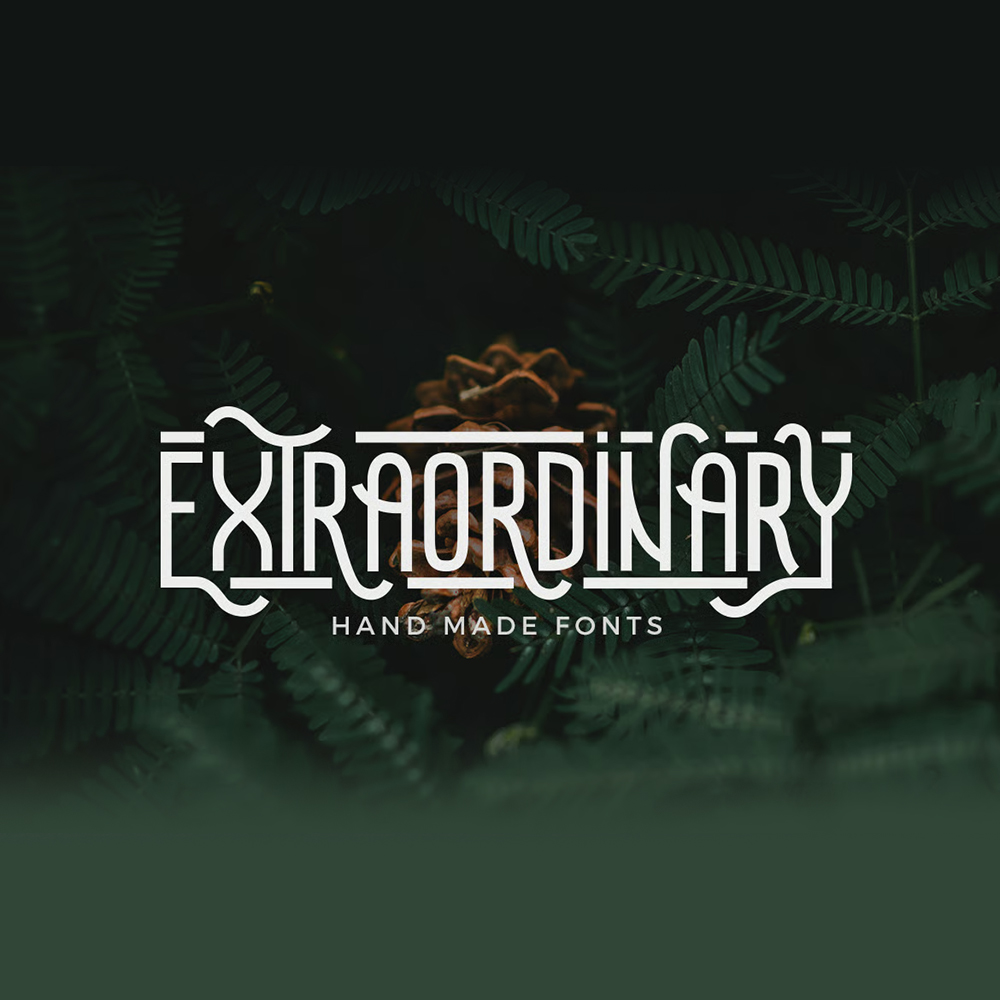
فونت پرمیوم و انگلیسی Extradionary Font یکی از بهترین فونتهای دستنویس ارائه شده میباشد. Extradionary ایدهآل برای لوگو، سربرگ، عنوان، چاپ و سایر کارهای خلاقانه که با استفاده از این بسته فونت دستساز فوقالعاده، نتایج تایپوگرافی، حروفنگاری فوقالعادهای میتوانید خلق کنید.
مزایای استفاده از فونت لاتین Extradionary Ballerina چیست؟